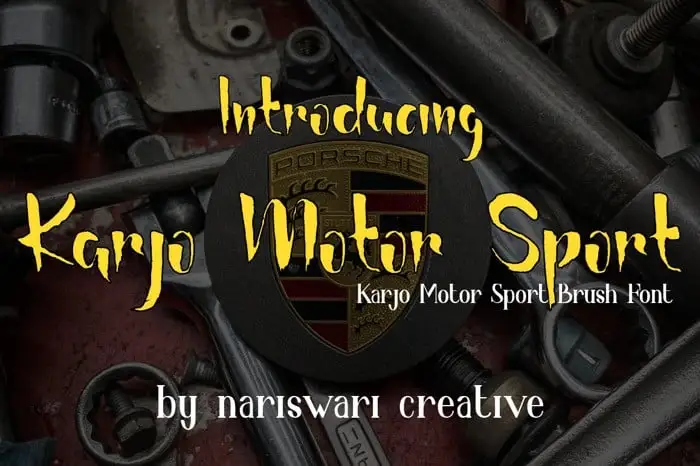
Karjo Motor Sport Script Font – Download Grátis
A Karjo Motor Sport Script Font é uma tipografia escrita a mão com traços suaves e moderna, criada pela Nariswari Creative. Ela traz consigo um caracter distintivo que se destaca perfeitamente para projetos diversos, como logotipos, panfletos, selos de identidade, capas de livros, camisetas personalizadas ou embalagens. Sua versão OpenType oferece opções incríveis, incluindo alternativas estilísticas, conjuntos estilísticos e ligaduras que tornam o processo criativo muito mais flexível e eficiente. Esta fonte é perfeita para designers que buscam um gráfico suave com estilo motorizado, ideal tanto para criação de logotipos quanto para ilustrações ambulantes e designs em massa.